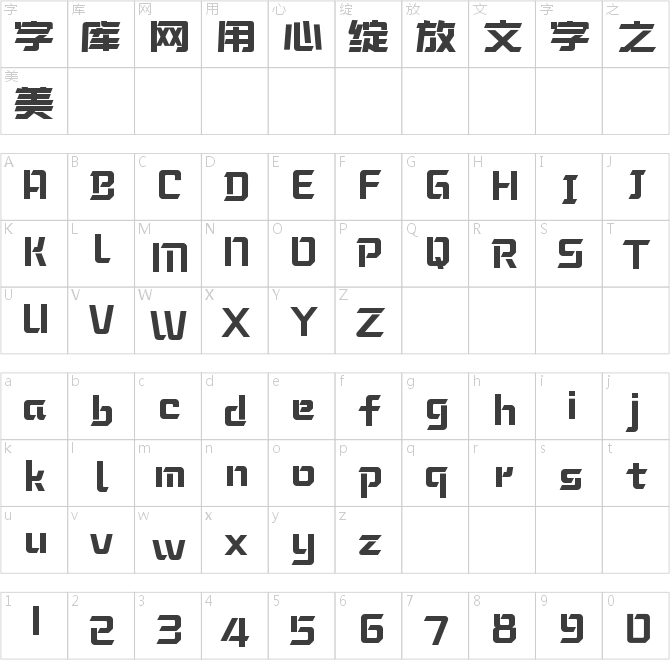
造字工房凌黑體 詳情頁
字體名稱: 造字工房凌黑體
造字工房凌黑體
造字工房凌黑體介紹
造字工房凌黑體字體字庫是一款讓人賞心悅目、百看不厭的中文字體,適合各類廣告和產(chǎn)品包裝設(shè)計應(yīng)用,字體大小3.99MB,格式為ttf字體,上傳用戶是星期一,作者/版權(quán)方為造字工房